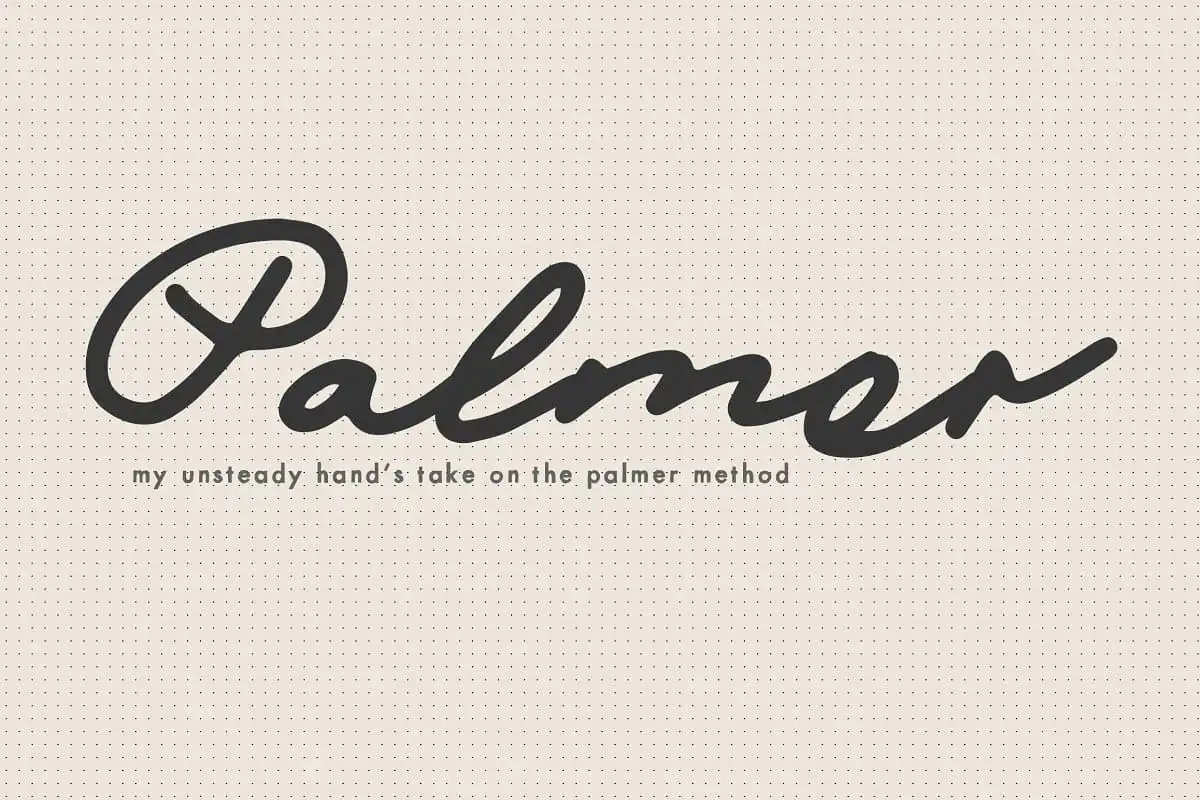
Mix Palmer Script Font – Download Grátis
Introduzimos a Mix Palmer Font, projetada pelo Mikko Sumulong e disponível gratuitamente para download na Creativemarket. Esta font é perfeitamente adequada para criar uma aparência bem desenho, ideal tanto para cartas de casamento quanto para estilos de design único e autêntico. A Mix Palmer é a minha versão suave e instável do método palmer, um estilo que permite a criação de uma aparência aparentemente esquisita. Especificamente projetada para criar um aspecto aproximado da escrita, essa fonte oferece uma solução perfeita para diversas necessidades, incluindo cartões de postais de casamento, logotipos criativos e únicos, materiais de blog e estaçãoaria, mensagens comerciais, revistas e muito mais. A Mix Palmer é um recurso ideal para quem busca um visual de design autêntico. A sua aparência descompromissada combina perfeitamente com diferentes estilos de apresentação e pode ser facilmente combinada com outros tipos de fontes para obter resultados inovadores e criativos.